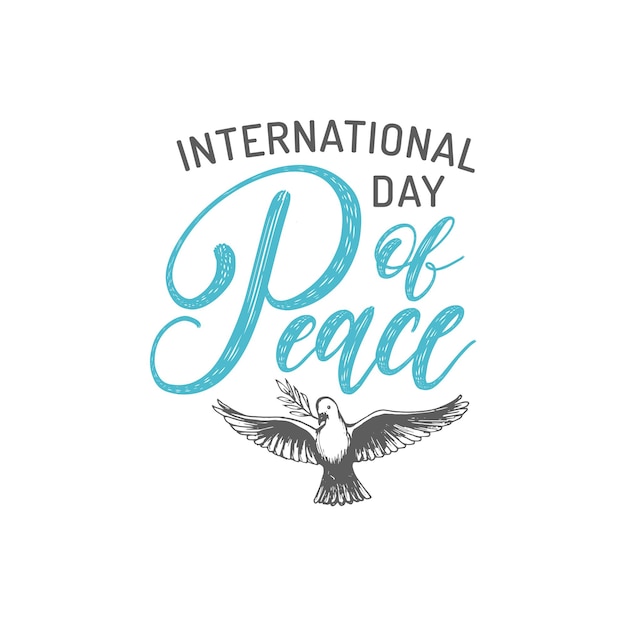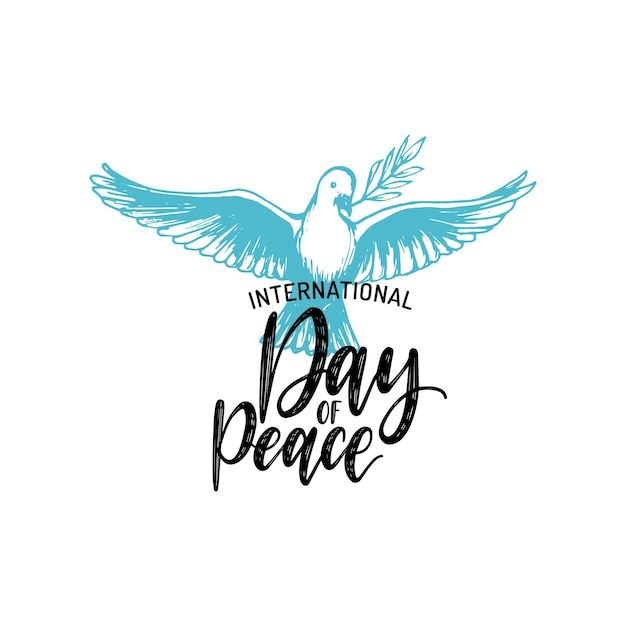
Plakat Światowego Dnia Pokoju z odręczną czcionką Ilustracja wektorowa narysowanego gołębia z gałązką palmową Kartka świąteczna
Międzynarodowy Dzień Pokoju, wektor strony napis. Rysowane ilustracja gołąb z gałązką palmową na białym tle. Kartka świąteczna, plakat z kaligrafią.